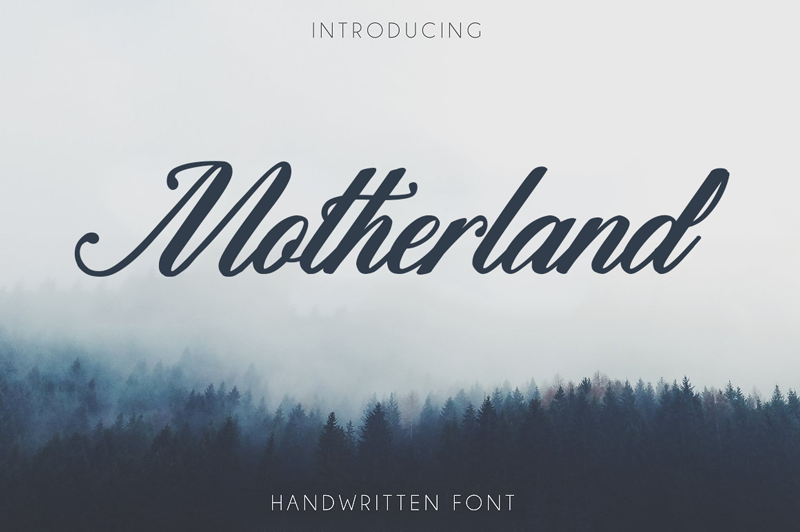
Motherland Font
A Motherland Font é uma elegante fonte script que transmite um ar intimista e sofisticado, perfeita para criações pessoais ou até mesmo para trabalhos artísticos que não envolvam conteúdo sexual. Através deste design único, você pode transformar qualquer projeto em algo ainda mais singular. Seu designer, Cat Butcher, criou uma fonte de qualidade que valoriza a autenticidade e o encanto da letra. Ideal para nomes de empresas, cartões de visita ou até mesmo projetos pessoais como ilustrações ou gráficos, a Motherland Font oferece um tom suave e envolvente sem perder em elegância. Se você quer incorporar essa font à sua criação personalizada ou está pensando em trabalhos comerciais usando ela, é essencial que entre em contato com Cat Butcher antes para garantir seu uso. Para obter o formato completo, basta enviar um e-mail para .